西文字体怎么看?怎么用(上篇)
在设计学习中,多了解相关的历史,可以让我们在了解旧事旧物的同时,还能得到新的感悟,从而为大家的综合能力添砖加瓦。为此我们专门开辟了一系列给设计师看的历史课程专栏。在之前,我已经给大家讲过了汉字的历史,和中国现代美术字的历程。今天我们不妨进一步拓宽视野,来共同探究西文字体的发展。
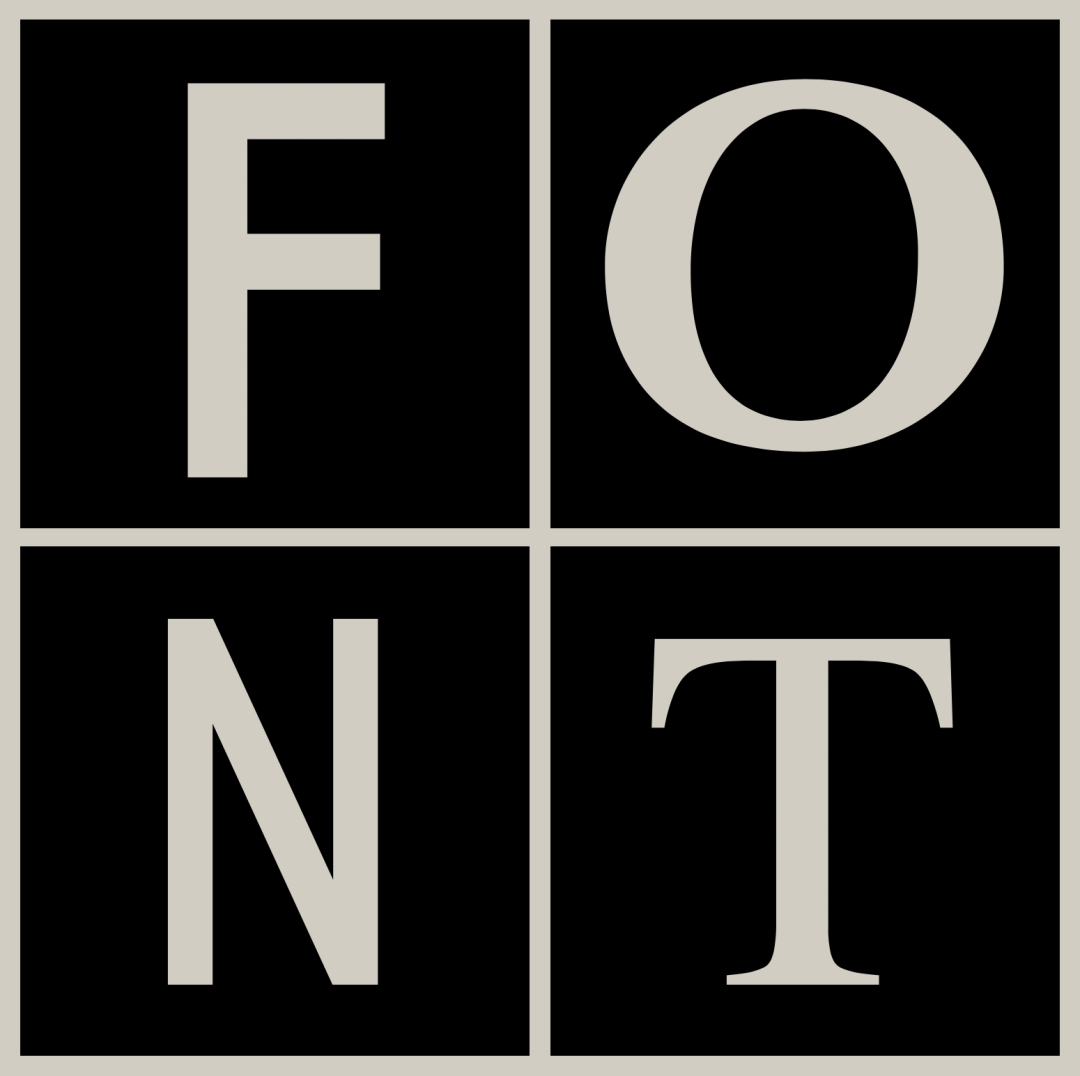
我们都知道,西文字体的数量非常丰富,如今早就已经超过了成千上万的体量。不过虽然选项丰富,但是许多人都不会去在意字体背后的故事了,可就是看似简单的一款字体,也有许多有趣的细节。
对于汉字,我们尚且还能够知道书体大致的演变轨迹,那西文又如何呢?其实西文字体可以说的地方同样一点也不少。
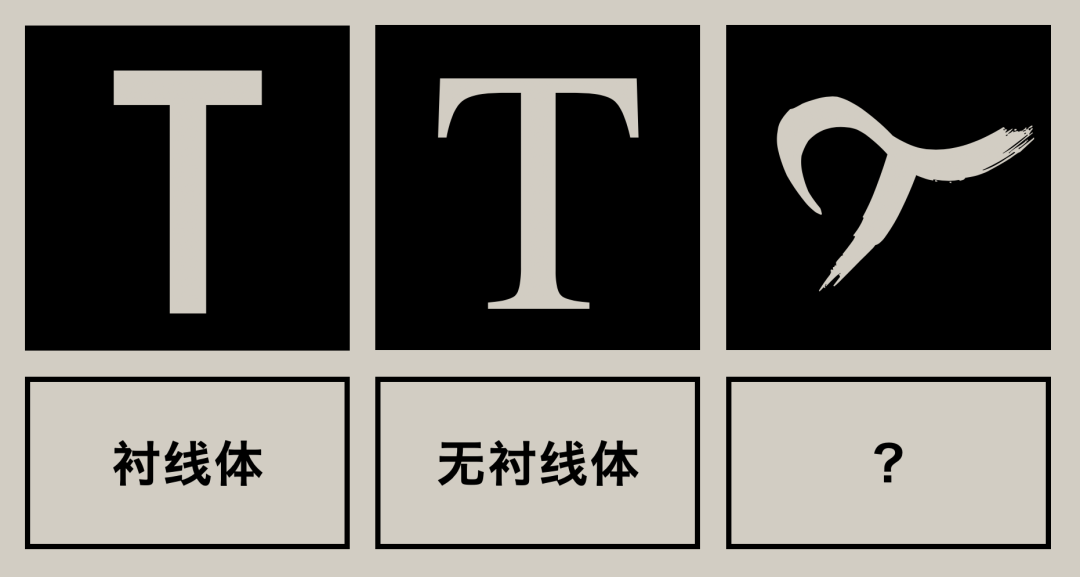
作为一名专业的设计师,如果只知道「无衬线体」和「衬线体」一定是不够的。除此之外我们还常会听到哥特体、草书体等等,它们在西文的发展历程中扮演着什么样的角色呢?
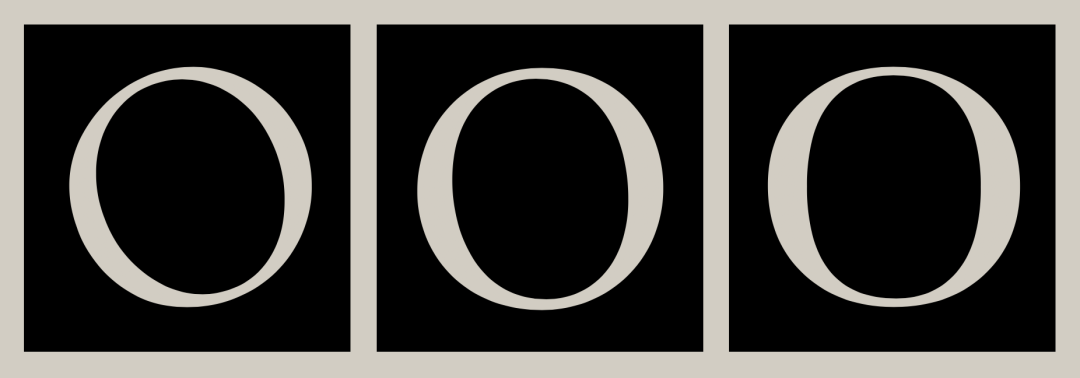
如果我们细心观察,还会发现,就算是同一类型的衬线体,我们也能看到许多不同的特征点,他们与历史又有什么样的关系呢?
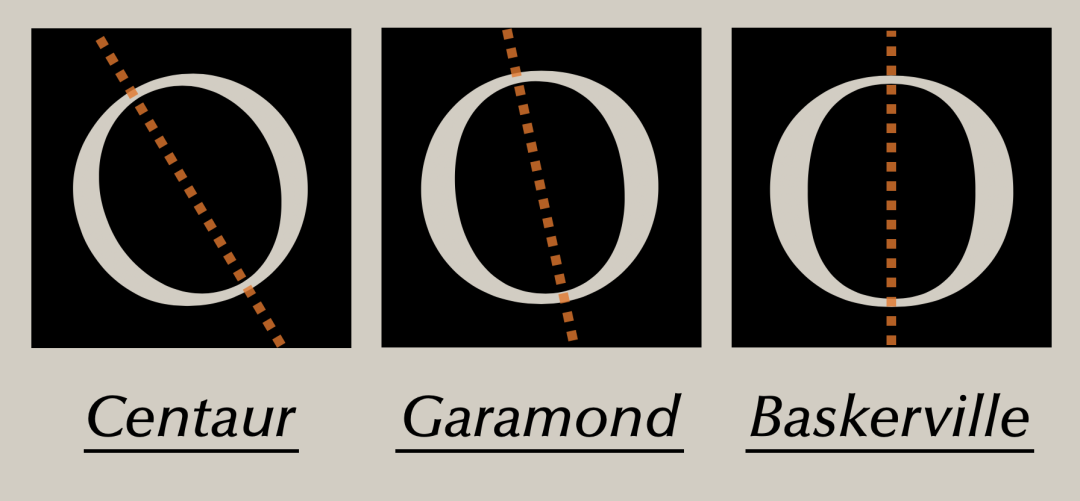
比如说,我们看这三款衬线体的字母「O」,实际上它们的中轴线的角度就有明显的变化,而这三款字体其实正是代表了衬线字体的几种不同风格和历史时期。
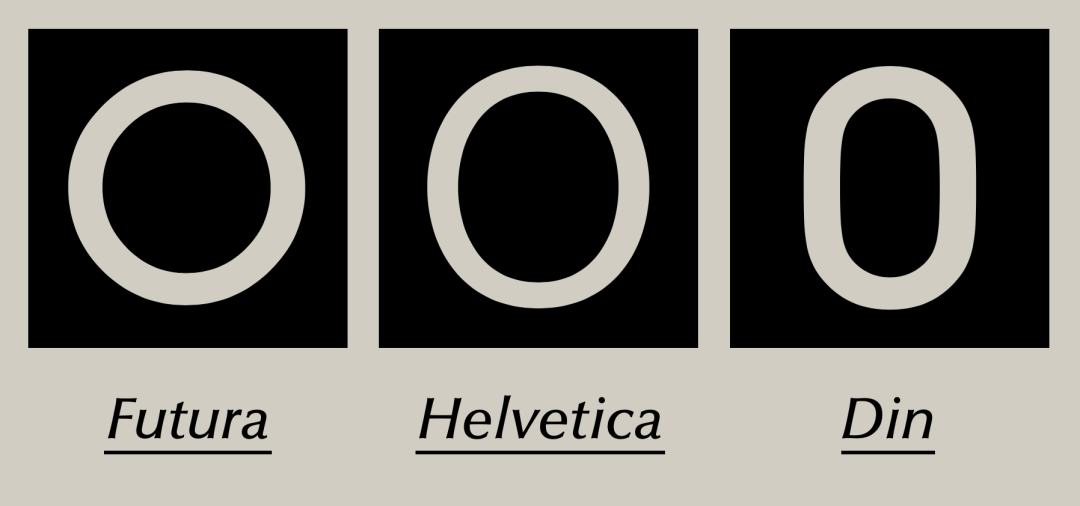
无独有偶,对于无衬线字体来说,这三款不同外形特征的字体也同样代表着一个时代或一种风格。如果我们可以完整的了解这些细节变化,那么驾驭各种风格的设计也会轻松许多。
除此之外,现在当我们选择一款字体时,可以随意地切换大小写,然而在历史上,实际是先有大写后有小写的。假如我们在设计一个时代背景是只有大写字母的画面时,错用了小写,那就显得不太专业了。尽管这没有绝对的对错,但是因为不了解而犯错一定是业余的表现。
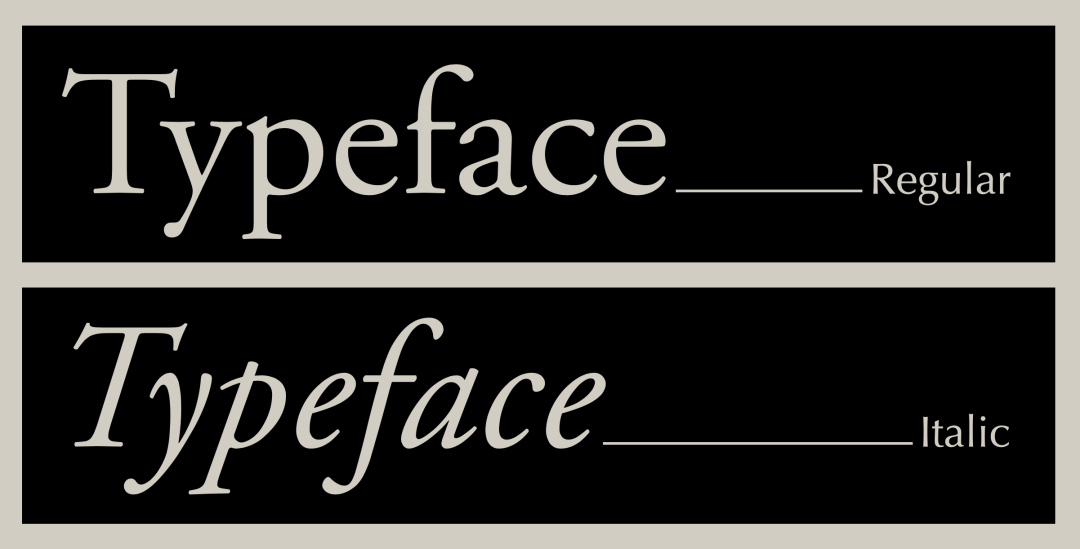
除了大小写的切换,很多字体在提供常规体的同时,还提供意大利斜体来丰富大家的排版选择,这种稍稍倾斜的字体实际上最初也是作为单独的字体而出现的。同样的,如果我们在做一个意大利斜体还没诞生的时期为背景的项目时,却使用了意大利斜体,也是容易闹出笑话的。
从上述的几个例子中不难看出,无论是做排版工作还是品牌设计,我们都需要了解一些西文字体的历史,来让我们表现得更加专业一些,往小了说,可以规避许多低级的错误,往大了讲,这会让我们设计的内涵脱颖而出。所以于情于理,我们都有必要学习更多关于西文字体的知识,了解这些也是相当于扩充了我们作为设计师的武器库。
前面有讲到,在历史上西文的大小写字母并不是一开始就是成双成对出现的,它有一个先后的出场顺序。
首先出现的字体类型叫作「帝国大写体」,它是来自罗马帝国的碑文字体。出现时间大约在公元前一世纪左右。在这个时期,还没有小写字母出现的。
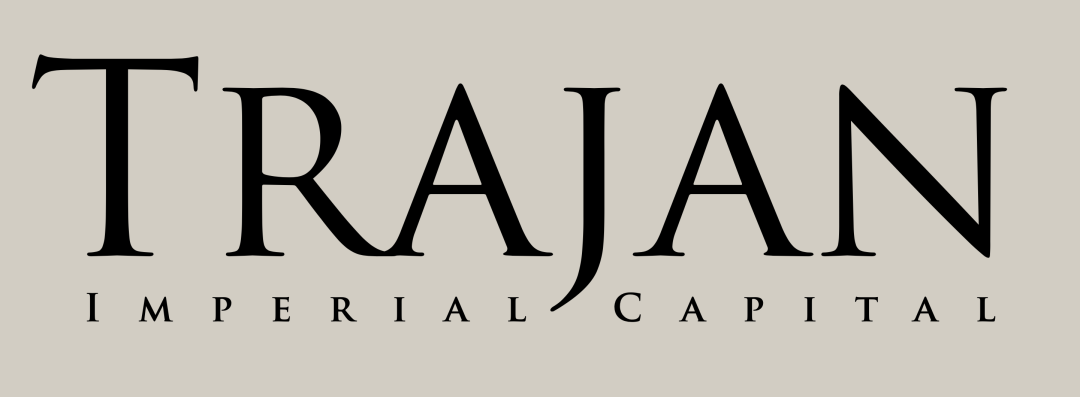
这类字体的代表当属「图拉真」字体了。我们可以看到,它本身并不配备小写字母,也是符合了时代特征的。
而「图拉真」这个字体名,是来自和它同名的一位古罗马皇帝,因为名字比较长,我们简称他为「图拉真」。图拉真在位时曾立下显赫的战功,罗马帝国的版图也在他的统治下达到了巅峰。
为了纪念这场战争胜利,罗马人兴建了一座纪念碑。而正是这座 44 米高的大圆柱基座上的碑文,成了「帝国大写体」的标志性文字。
后来这上面的字就被复刻成了现在我们所见到的「Trajan」字体。但是我们需要注意,这种字体并不是直接在石碑上雕刻成型的。
举个例子,我们看这里的字母「P」,它是由三笔完成的。工匠心里有着每个文字的造型,然后使用平头笔,按照顺序一笔一笔画出来,最后再根据绘制好的文字雕刻成型。
从这个步骤我们可以知道,虽然帝国大写体看起来简洁大方,但并不是个纯雕刻字,其实观察笔画细节,就能看到许多只有因为书写才会形成的特点。
比如我们倒推这里衬线形成的过程,它就是因为书写才形成了一个小凹槽,而这种带有小凹槽的衬线也正是这种类型字体的特征之一。
说到书写,我们就可以回到文章序言里所说的字母中轴线的问题了。实际上不同角度的中轴线,也是因为书写的原因而造成的。
比如说字母O,它就是用平头笔以两笔写成的。不同的笔头角度会导致笔画最细的地方,也就是起笔和落笔的位置有所差异,比如说,当笔头角度变为90度时,可能最细的地方就在中间了,只不过基本见不到在这个位置起笔的字体罢了。
书写者只要根据帝国大写体的样式,选择合适的工具依次画出两个弧线,这样,一个完整的字母O就完成了,其他字母也是以此类推的。所以说,轴线的角度和入笔时笔头的角度息息相关。
再说回图拉真,这款字体真的是一个深受电影和游戏界欢迎的字体,只要题材背景上点年纪、有史诗内味、或者主题比较宏大一点的,用这个字体基本就很难出错。比如说这里就有大家耳熟能详的《泰坦尼克号》,《权力的游戏》,《刺客信条》等等。
另外还有一款MOBA类电子竞技游戏「DOTA2」也是使用了「图拉真」为Logo标准字的原型。把Logo提取出来比较原字体,我们可以发现,这里「DOTA2」的Logo几乎与图拉真一模一样,只在字母「A」的地方做了一些个性化的修改。
所以说,对于这个时期风格的字体是否选用小写字母一定要慎重,比如说这款「Stempel Schneidler」字体尽管设计有小写字母,但是它本身其实就是属于这一时代感觉的字体,这是我们在设计应用时需要注意的。
说完了大写体,我们接着来讲小写体的诞生。卡洛林小写体是一种完全由小写字母而组成的字体。这时候时间已经来到了公元8世纪。
我们可以看到,除了部分字母和现在我们所熟知的小写字母不太一样以外,其他的几乎都相差无几。可以说卡洛林小写体本身就很有一种独特的复古韵味。
查理大帝是法兰克王国加洛林王朝的国王。他大幅扩张版图,统一了日耳曼各部,由教皇加冕为西罗马皇帝,从国王变为了大帝。 查理大帝在统一中央集权整备法制的同时召集了欧洲各地学者振兴学术文艺。这个文化繁荣的时期被史学家称为「卡洛林文艺复兴」。
查理大帝从约克叫来了高僧阿尔昆,并提拔他为图尔的圣马丁大修道院院长。阿尔昆在修道院里开设了抄写室,开始研发新的字体。
实际上,在卡洛林小写体之前已经出现了一些小写字母,比如由罗马时代后期的安色尔体发展而来的半安色尔体。而阿尔昆就是在半安色尔体的基础上继续进行改进的。
最终阿尔昆研发出了一种崭新的字体,这就是卡洛林小写体。到这里,小写字母就已经非常接近现在我们所使用的了。
到今天,卡洛林小写体的应用其实并不多见,相关的字库产品也同样很少。这款「Carolina」就是为数不多的复刻字体之一。
也许手写版本的卡洛林小写体,放到现在功能性已经比较落后了,而字库产品也终究既没有以前的味道,又现代化得不够坚决,显得模棱两可。这可能就是如今不多见的原因了。不过,卡洛林小写体其实本身有着诸多的后续变化。
让我们把时间推移到14世纪,这时候大家熟知的意大利斜体诞生了。当然了,这里我们所说的意大利斜体还属于一种单独的字体,或者说某种书写的具体风格。并不是现在各个字库产品中的家族成员了。
现在我们知道,帝国大写体确定了大写字母的书写规范,一直沿用到了现在。不过卡洛林小写体,虽然在已经非常接近,但仍然没有完全相同。
所以它又进一步发展到了人文主义小写体,这款书体行笔清晰,奠定了小写字母的基本结构,明确了手写和印刷字体的字形,与当时的文艺复兴运动相得益彰。然而,终究还是因为书写速度太慢而被进一步改造。
最终,意大利斜体在这样的背景下诞生了,由尼古拉·尼古力发明的这款书体省时省力,还被教皇法庭设为官方专用。人类的偷懒历史总是如此惊人的相似,我们的楷书和行书看了也是直呼内行。
如果单看「italic」这个词,总觉得就叫意大利体是完全没毛病,但是我们会更习惯的称呼为「意大利斜体」,原因就是在于,字母全部微微倾斜是这款书体的第一大特征。
究其原因我们不难发现,当我们在书写时,为了追求速度势必会产生这种倾斜,不仅西文字体如此,其实汉字也是一样的,只不过汉字是笔画向上倾斜,而结构上并不会。
除了向右倾斜以外,意大利斜体还有几个明显的特征。他们的关键词分别是:椭圆、一笔、相接。
先来讲「椭圆」,通过图中常规体与意大利体的比较我们可以看出,字母中本来的圆形笔画在意大利斜体下,会变得趋向于椭圆形。
至于「一笔」和「相接」,我们可以放在一起来讲,我们看这张意大利体的手稿,不难发现,为了方便速写,许多字母都可以用一笔写成,并且,许多字母与字母之前也会用连笔相接。
了解了意大利体的由来和特点,分清现在字体家族里常见的Italic和Oblique就变得更加简单了。
为了方便竖向比较我们可以再拿出他们各自的常规体。首先我们可以看到,虽然两种倾斜体都有向右微微倾斜的特点,但是意大利斜体因为出生原因天然就带有手写感,而普通的倾斜体只是机械地将文字倾斜处理而已。可以说一种倾斜是自然而然的,另一种是强行附加的。
再通过纵向来看的话,我们发现,同一款字里的意大利斜体比起常规体会显得笔画更细,整体排印下来文字组的长度也会更短。不难想象,如果在一片常规体的正文中忽然用到意大利体,将会是非常醒目的。
而普通的倾斜体和常规体相比较,笔画上并没有粗细的变化,长度也是基本一致。毕竟,这只是单纯的对字进行了倾斜处理而已。
意大利斜体在设计中的应用非常丰富,关于这一块我们可以从两方面来简单说一下,首先来看应用案例。
意大利斜体现在作为字库家族的一员,在设计中出现的频率还是非常高的,我们很难说是出于某种气质来用意大利斜体了,因为包含意大利斜体的字体也是多的数不过来,就不可能找出风格上的规律了。倒不如说,意大利斜体在设计上的应用,首先就是丰富了各个字库产品的家族系统。
当然,在设计中意大利体确实有一些妙用,比如说在编排文字时,使用意大利体可以在字号、字重、颜色不变的情况下与常规体产生节奏变化从而起到对比的效果,善加利用可以让版面更加具备层次感,而又不会破坏统一性。
除此之外,我们也还能看到很多优秀作品,在面对一些在短句中出现的「of」、「the」、「a」等词时,常常会将这些词替换成意大利斜体来与其他更具备实际意义的单词形成区别,这里实际上也是利用了对比的效果。